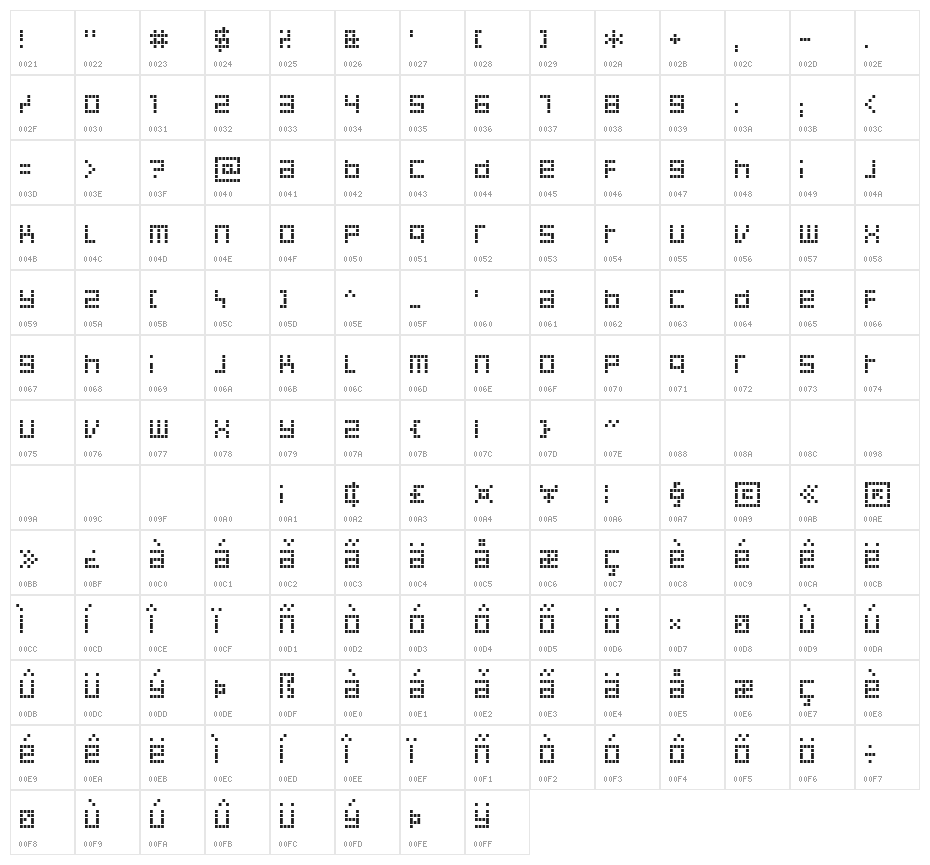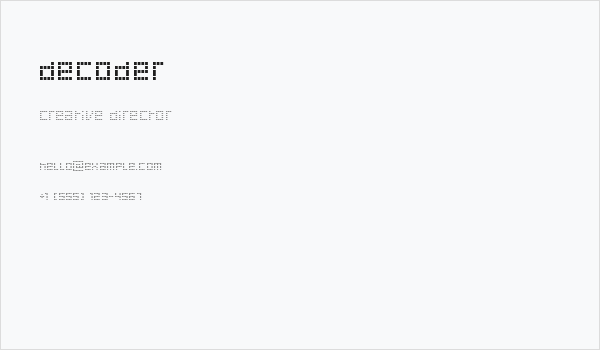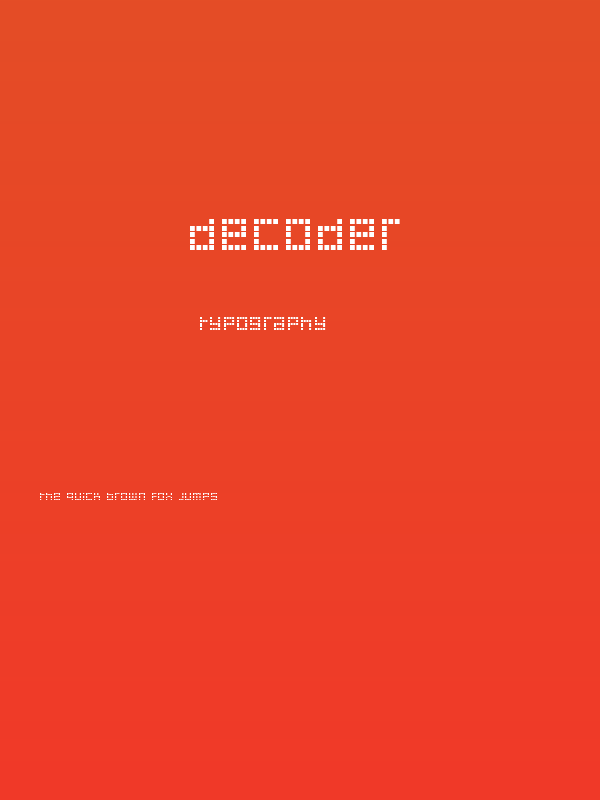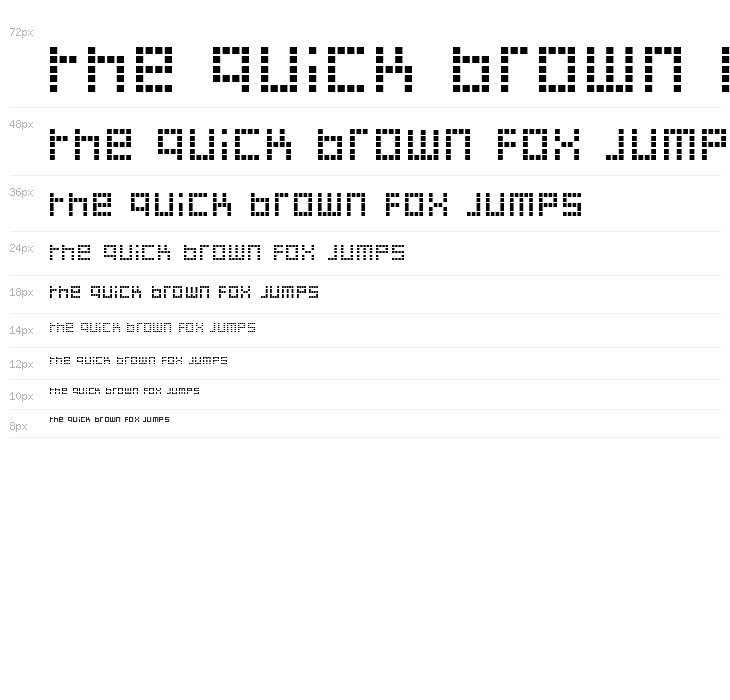
Decoder Font
✎ Dotted
| Stil general | Retro, Digital |
| Caz de utilizare | Headlines, Logos, Digital Art |
| Proiecte propuse | Ideal for retro-themed designs, video game graphics, tech-inspired branding, or digital art projects. |